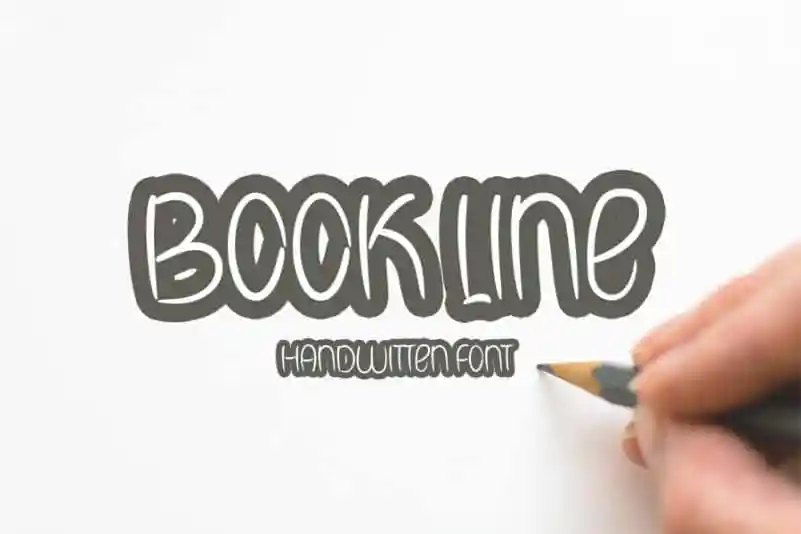
Book Line Script Font
A Book Line Script Font é uma elegante fonte escrita a mão com estilo descontraído. Com um toque casual e sofisticado que combina perfeitamente entre as mais variadas tarefas de design, seja para projetos de marca, headings, designs de casamento, convites, assinaturas, logotipos ou rótulos. Seja qual for a causa, essa fonte vai transformar qualquer projeto num toque especial e elegante que destacará sua criação entre os demais. Ideal para designers que desejam adicionar um toque autêntico e divertido em seus projetos, seja em uma empresa de design ou na personalização dos mais variados itens domésticos. A Book Line Script Font é a escolha perfeita para quem busca criar algo singular e único, sem perder o cuidado que caracteriza as fontes a mão. Esta fonte escrita a mão apresenta um estilo confortável e versátil, combinando elegância com personalidade. Com inermediaSTUDIO como designer, podemos esperar uma fonte de alta qualidade e flexibilidade. Este é o tipo de fonte ideal para quem deseja adicionar um toque autêntico ao design, seja num projeto de marca ambicioso ou em detalhes pessoais.